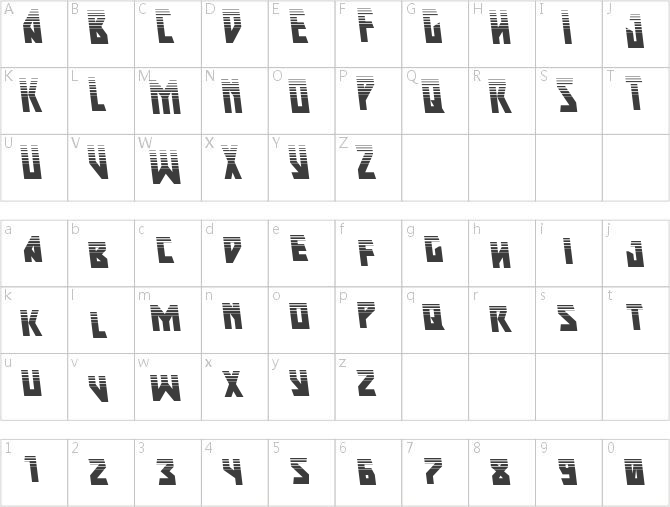
Major Force Halftone Leftalic
Major Force Halftone Leftalic介紹
Major Force Halftone Leftalic字體字庫是一款讓人賞心悅目、百看不厭的英文字體,適合各類廣告和產品包裝設計應用,字體大小0.03MB,格式為ttf字體,上傳用戶是誠澤永信,作者/版權方為未知